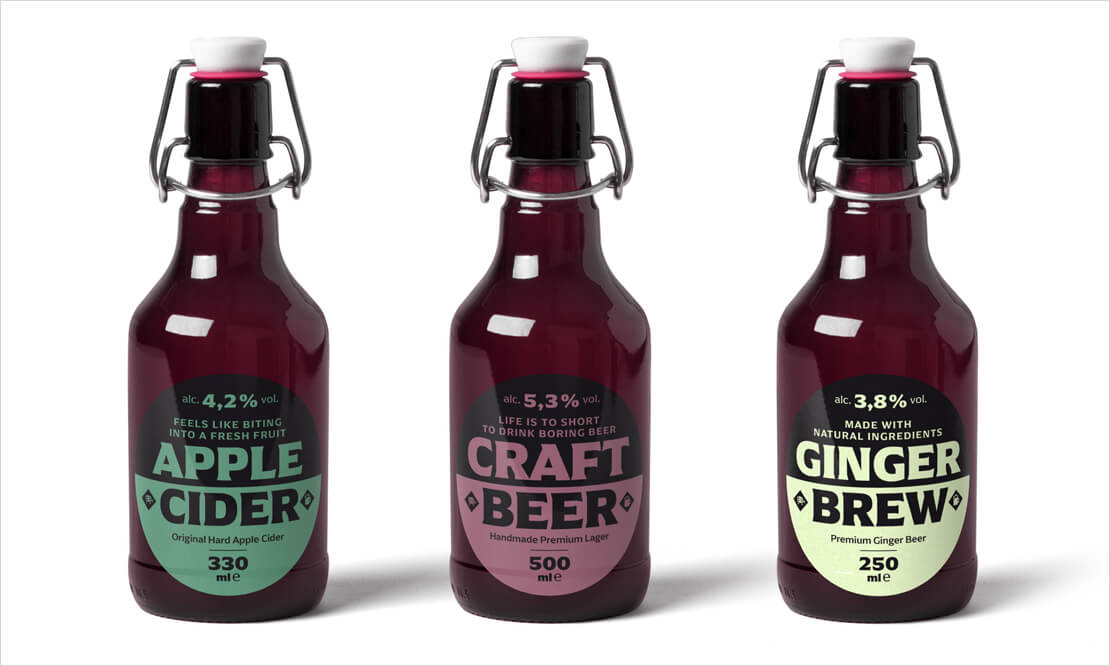
»Arpona« von Felix Braden
Der Designer Felix Braden hat seine neue Schriftfamilie vorgestellt. Die Schnitte von »Arpona« enthalten dezente Dreiecks-Serifen, die für ein charaktervolles Erscheinungsbild sorgen.
»Arpona« ist inspiriert von den in Stein gemeißelten Buchstaben der römischen Antiqua. Die Schriftfamilie lässt sich ansonsten aber nur schwer in Kategorien einordnen. Sie ist weder eine Serifenschrift noch eine Serifenlose, sondern vielmehr eine Symbiose verschiedener Designkonzepte. Aufgrund ihrer Plakativität eignet sich »Arpona« unter anderem für Packaging, Werbung, Editorial-Design etc. und lässt sich darüber hinaus auch im Fließtext auf dem Bildschirm einsetzen.
Die Familie hat 18 Schnitte, von Thin bis Black, inklusive entsprechender Kursiven. Jeder Schnitt umfasst 590 Glyphen und unterstützt alle west-, ost- und mitteleuropäischen Sprachen, darunter vier verschiedene Zahlensätze sowie viele Währungszeichen.
Entwurfsprozess der Schriftfamilie »Arpona«
Bei all seinen Schriftentwürfen beginnt Felix Braden mit einer handgezeichneten Skizze. Auch bei »Arpona« hatte der Designer eine grobe Idee im Kopf, aber noch keine Ahnung, wie die konkreten Buchstabenformen aussehen sollten. Freie, schnell gezeichnete Ideenskizzen haben dabei geholfen, eine Form zu finden.
Bei der Arbeit an »Arpona« war außerdem das Römisch-Germanische Museum in Köln eine wertvolle Inspirationsquelle gewesen, denn dort gibt es unzählige antike Steine mit römischen Inschriften. Felix Braden faszinierte besonders die, die nicht dem Ideal entsprechen, bei denen man die verwendeten Werkzeuge und Materialien erkennen kann. »Stein lässt sich nicht einfach bearbeiten, und Hammer und Meißel sind keine filigranen Werkzeuge. Man muss Gewalt anwenden, um sie zu nutzen, und Fehler können nicht korrigiert werden.«, so der Kreative.
Auch der Entwurfsprozess der ersten humanistischen Sans von Edward Johnston und Eric Gill für die Londoner U-Bahn war eine wertvolle Inspirationsquelle gewesen.
Als sich aus den Ideen eine Richtung herauskristallisierte, begann Felix Braden zu testen, ob das Konzept als ganzes Alphabet oder sogar als komplette Familie tragfähig ist. Auch hier war für den Kreativen die handgezeichnete Skizze der schnellste und effektivste Weg der Umsetzung. Erst als die Buchstaben im Text getestet werden sollten, begann er mit der Digitalisierung der ersten Glyphen.
Als sich schließlich die Schriftart im Fließtext bewährt hatte, gingen die Planungen als Schriftfamilie weiter. Die Master für das Interpolieren und die Anzahl und Gewichtung der Stile wurden festgelegt. Schließlich wurden die Buchstaben so lange digital überarbeitet und getestet, bis alle Zeichen harmonisch zueinander passten und ein klares und ruhiges Schriftbild entstand.